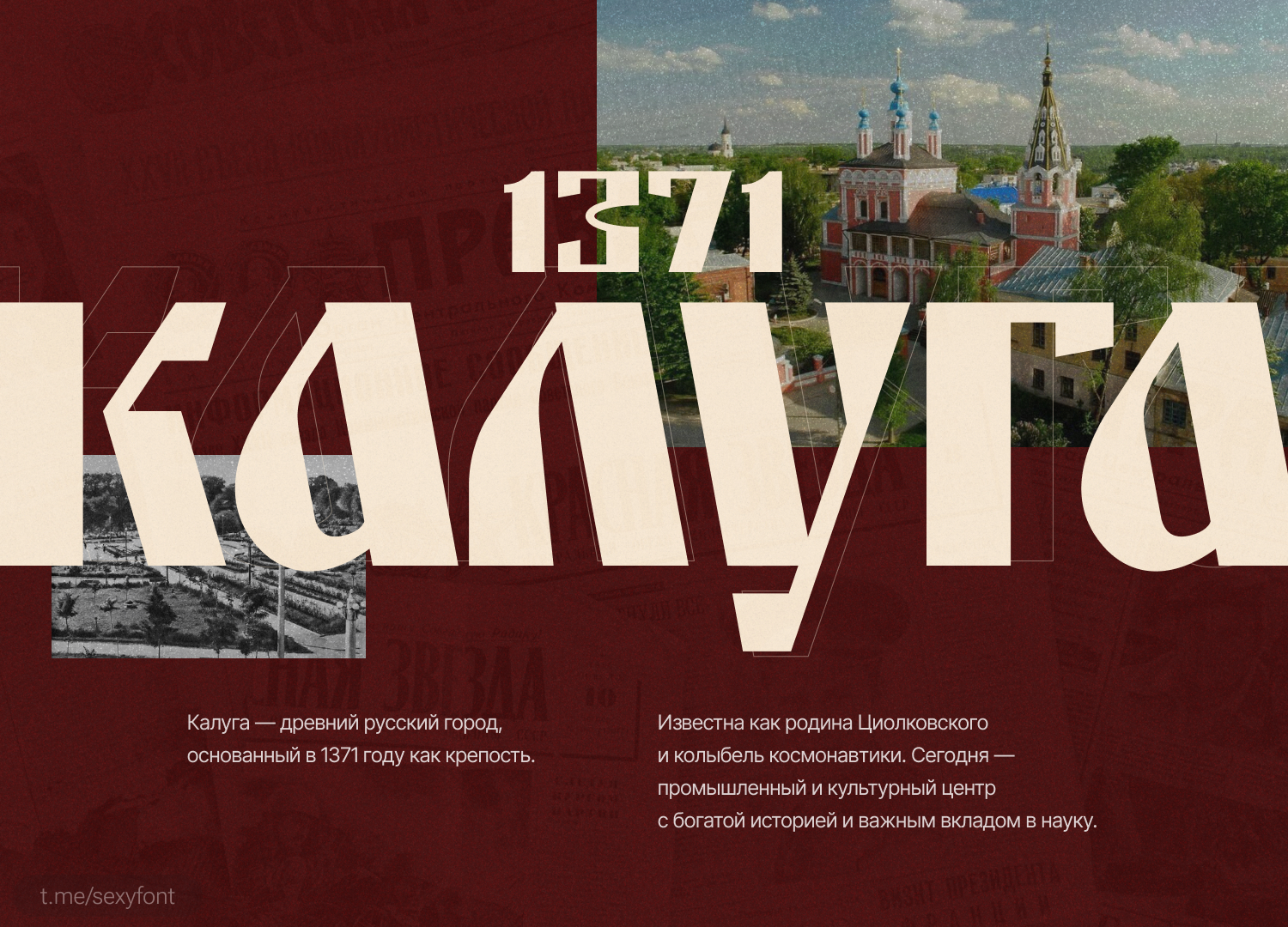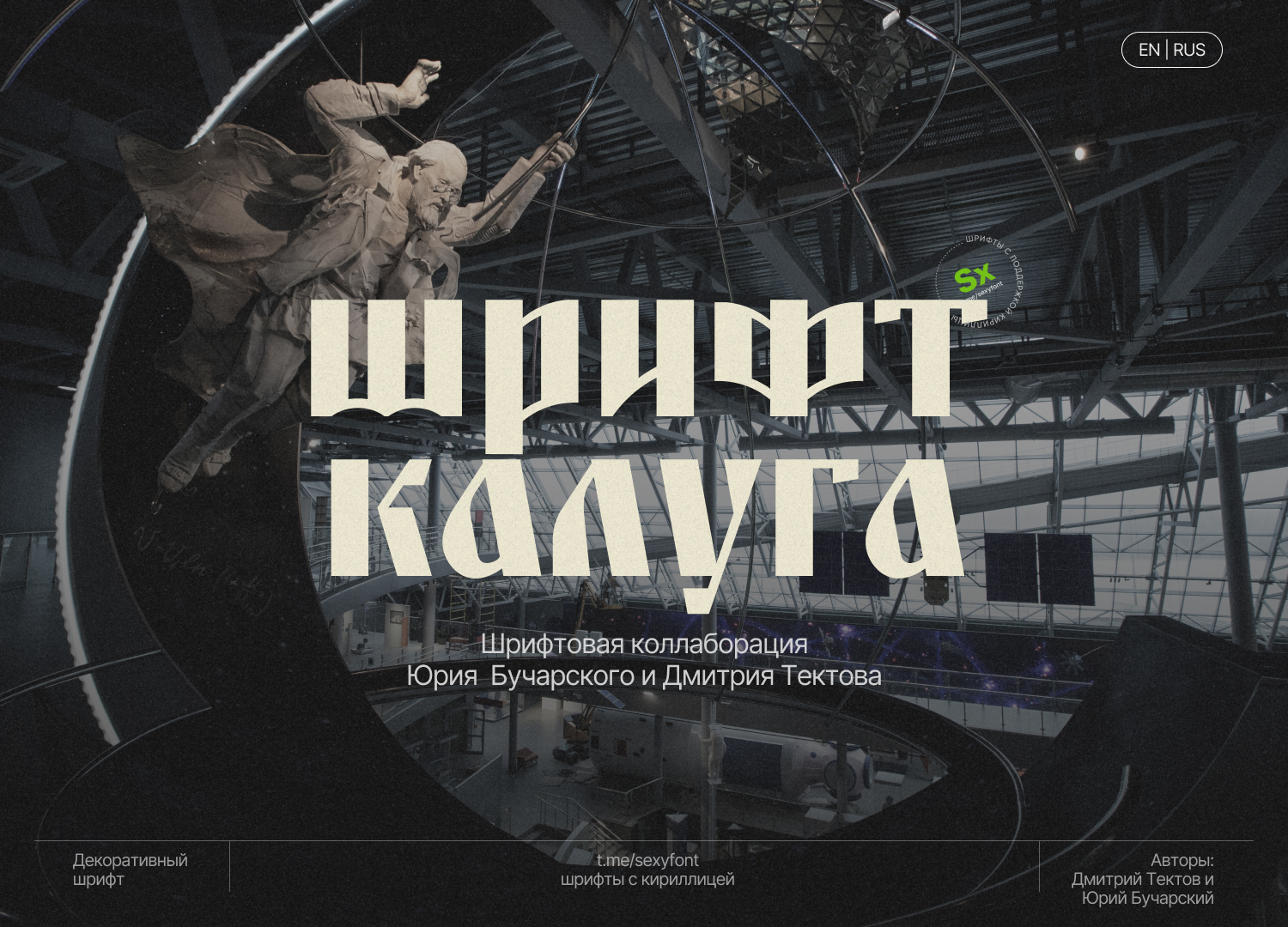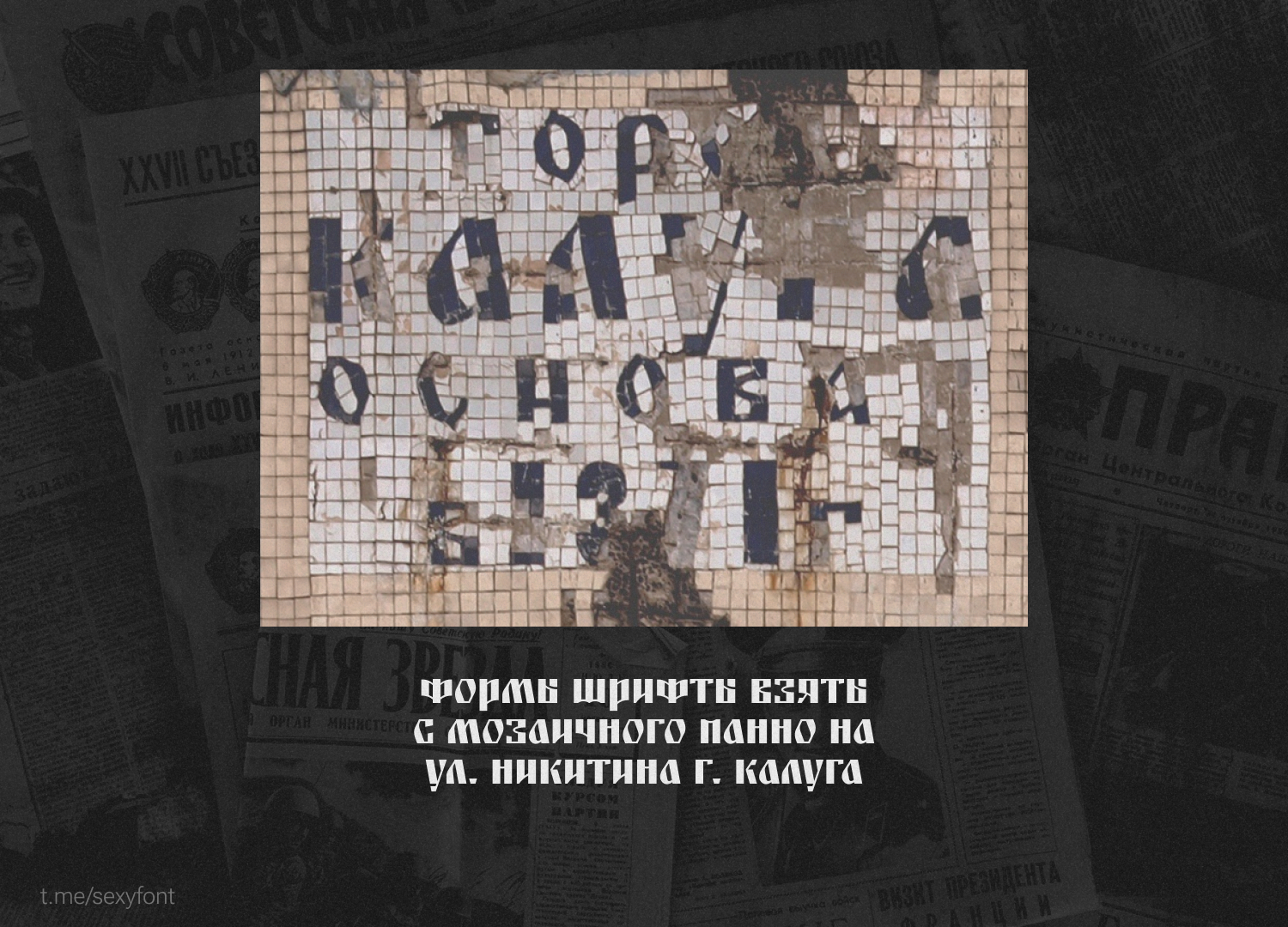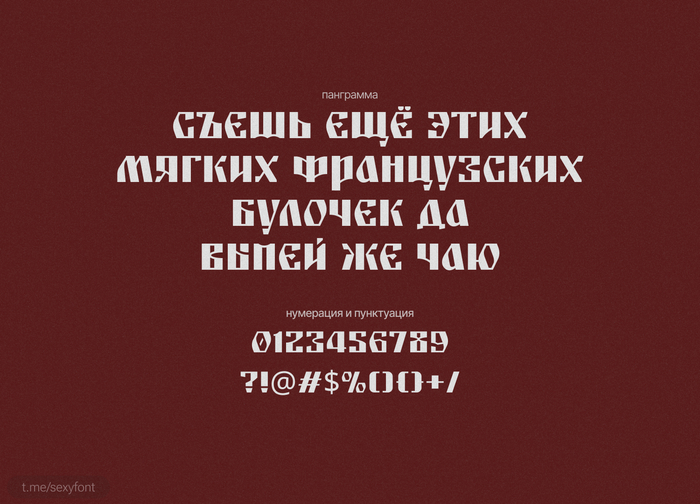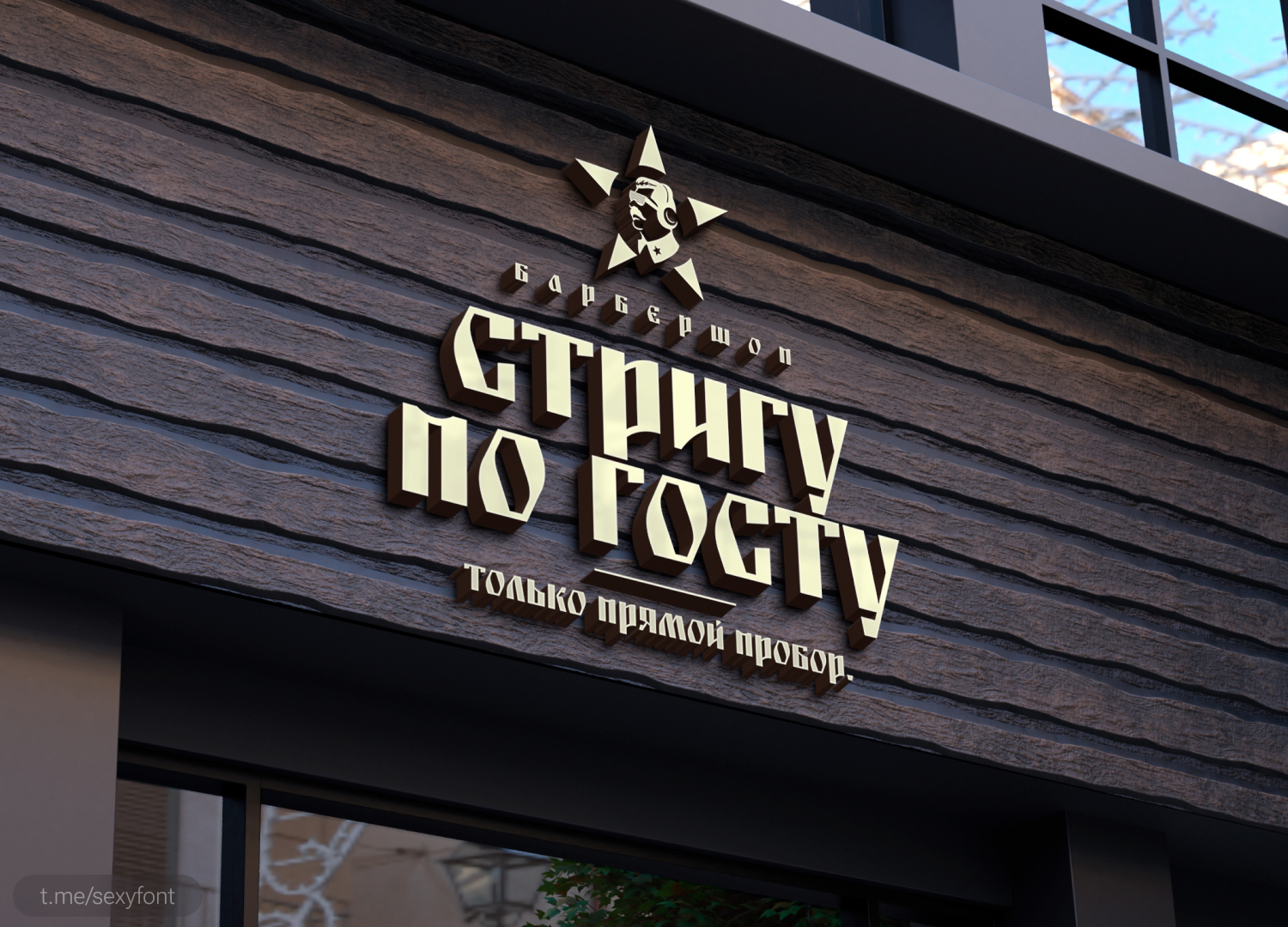
Шрифт Kaluga
Бесплатный акцидентный шрифт «Калуга». Формы шрифта взяты с мозаичного панно в г. Калуга. Для афиш, театров, исторических проектов, брендов с характером. Прямолинейный, но не скучный. Авторы: Юрий Бучарский и Дмитрий Тектов